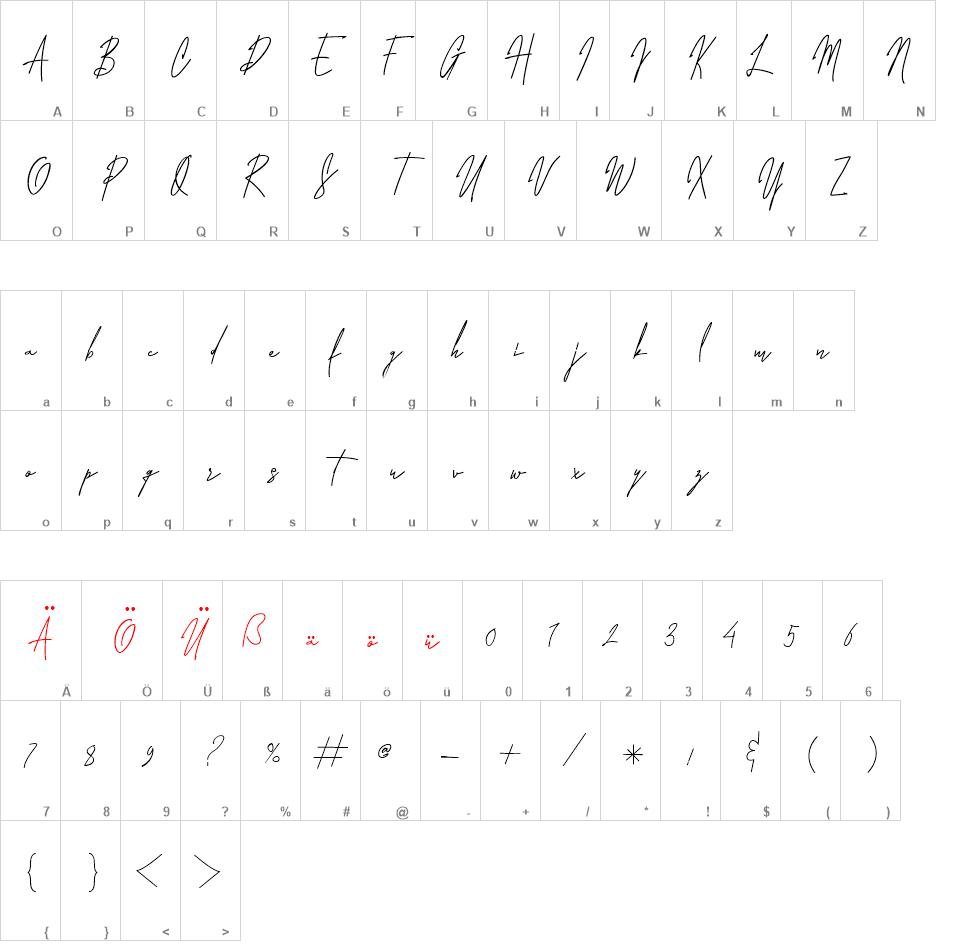
Laura Hellaw
Laura Hellaw eine schöne Schrift, Dies ist perfekt für Einladungen, Unterschriften, Blogs, Social Media, Visitenkarten, Produktmarken usw.
Creative Signature hat Style-Standard, Alternate Stylistic und Ligaturen. und enthält Groß- und Kleinbuchstaben, Zahlen und Interpunktionszeichen abwechselnd